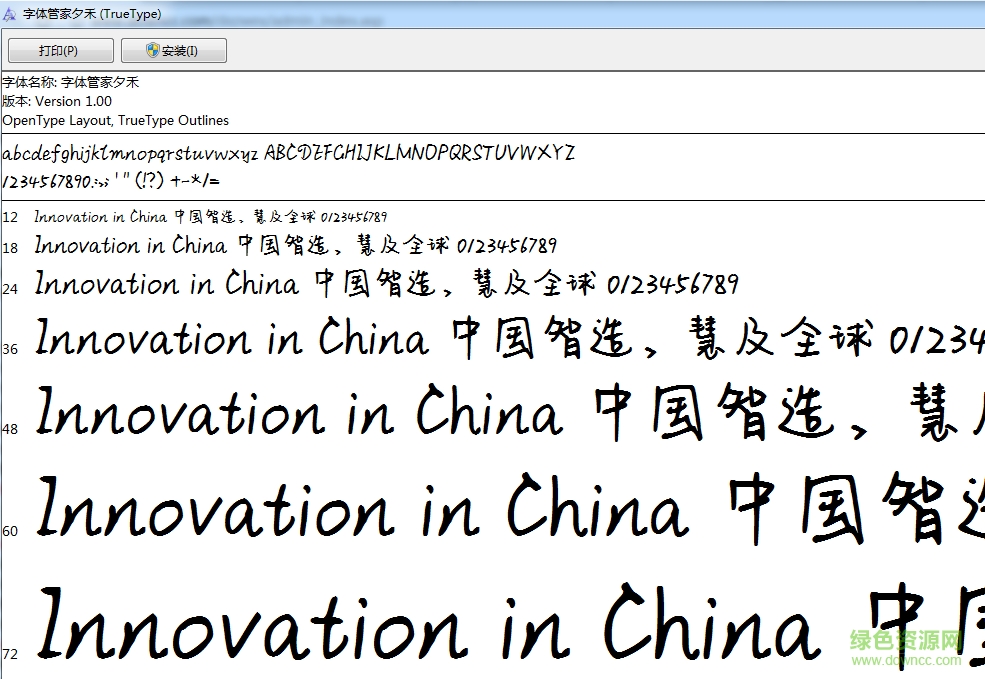
aa夕禾字體是一款根據(jù)首先字體設(shè)計(jì)而來的電腦字體,完美的繼承手寫體優(yōu)美,字形灑脫的特點(diǎn),非常用來廣告計(jì)、藝術(shù)創(chuàng)作、平面設(shè)計(jì)、印刷包裝、個(gè)性簽名等領(lǐng)域,有需要?dú)g迎來綠色資源網(wǎng)下載!
aa夕禾字體是一個(gè)姑娘的手寫字,這款字的靈感來源于作者的青春年少時(shí)光,讓人不禁回想起躲在墻后默默暗戀的日子。我希望和你在一起,如果不可以,那我就在你看不見的地方,永遠(yuǎn)陪著你 。那年我們還很青澀、懵懂,但是很美好。